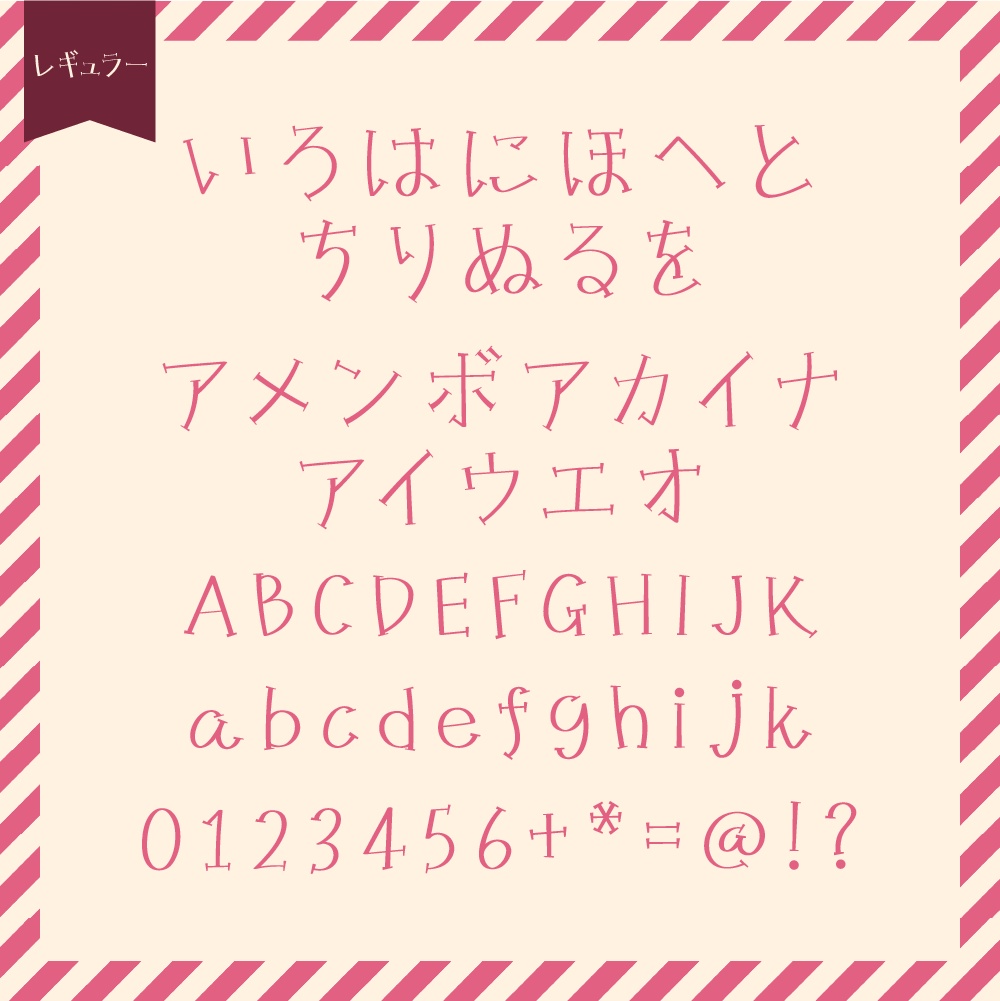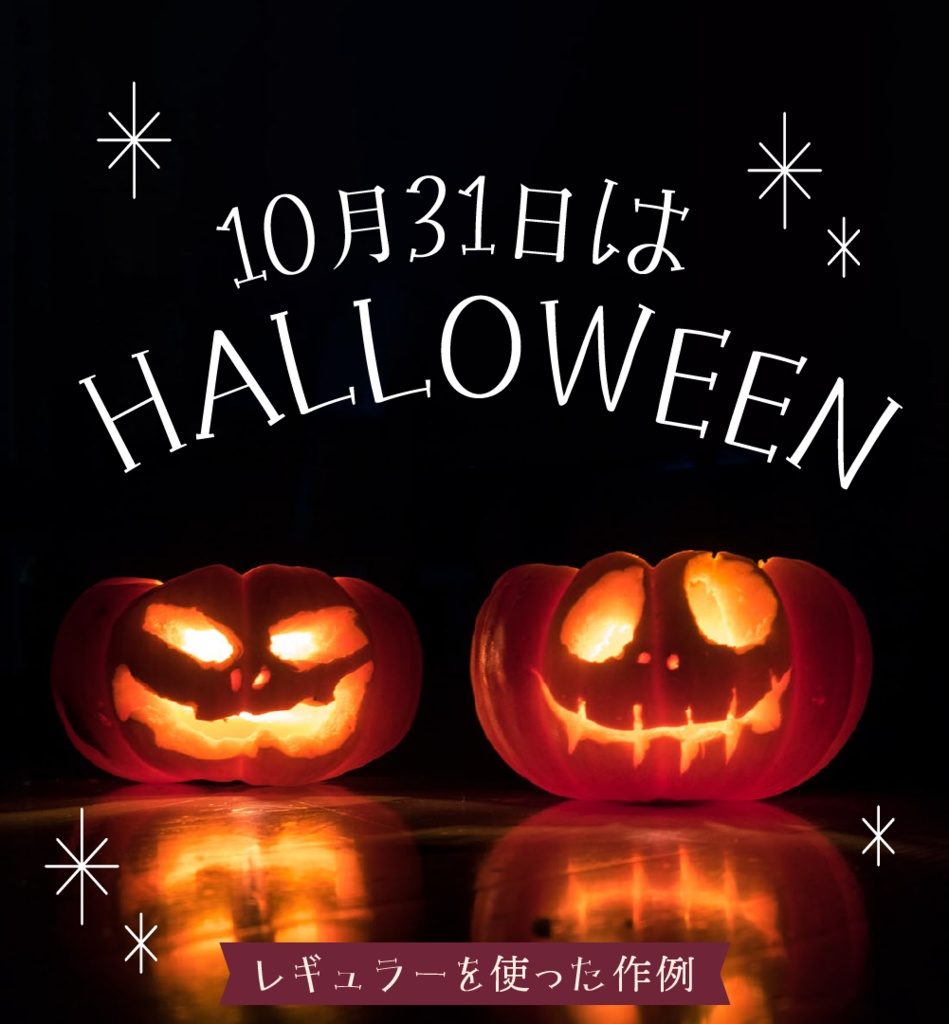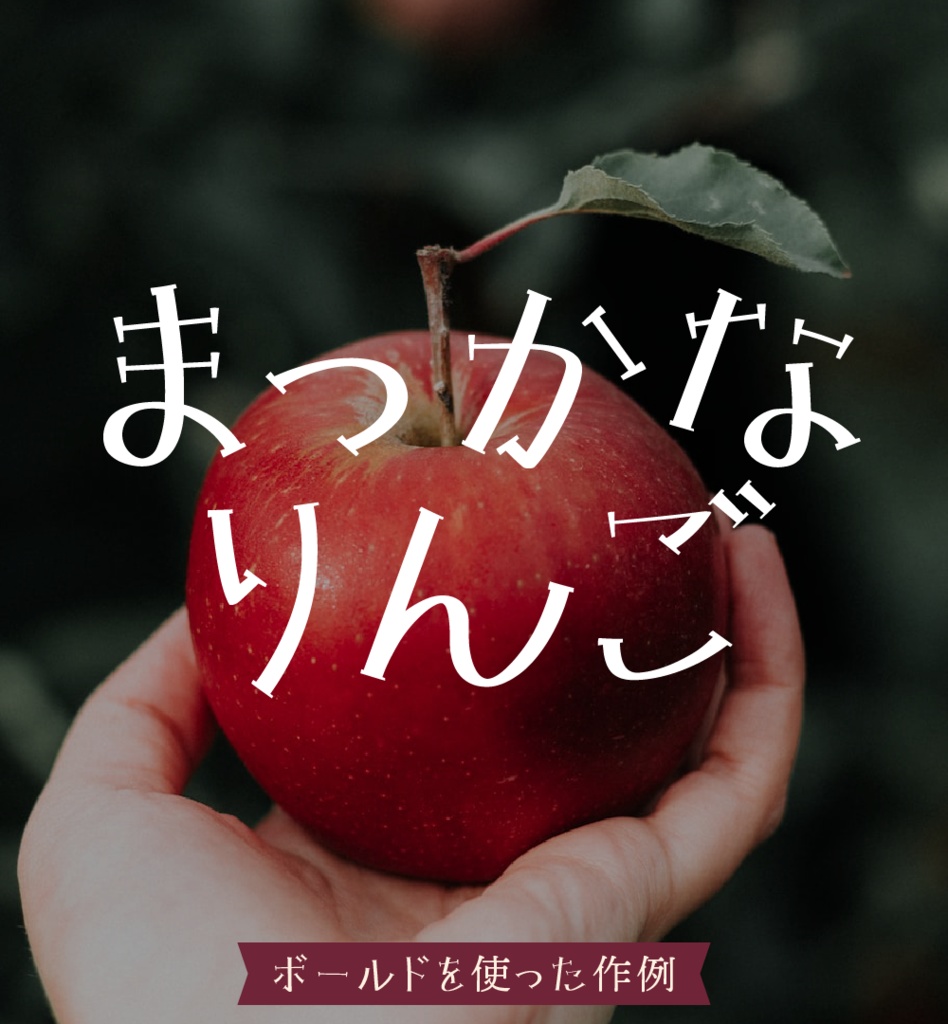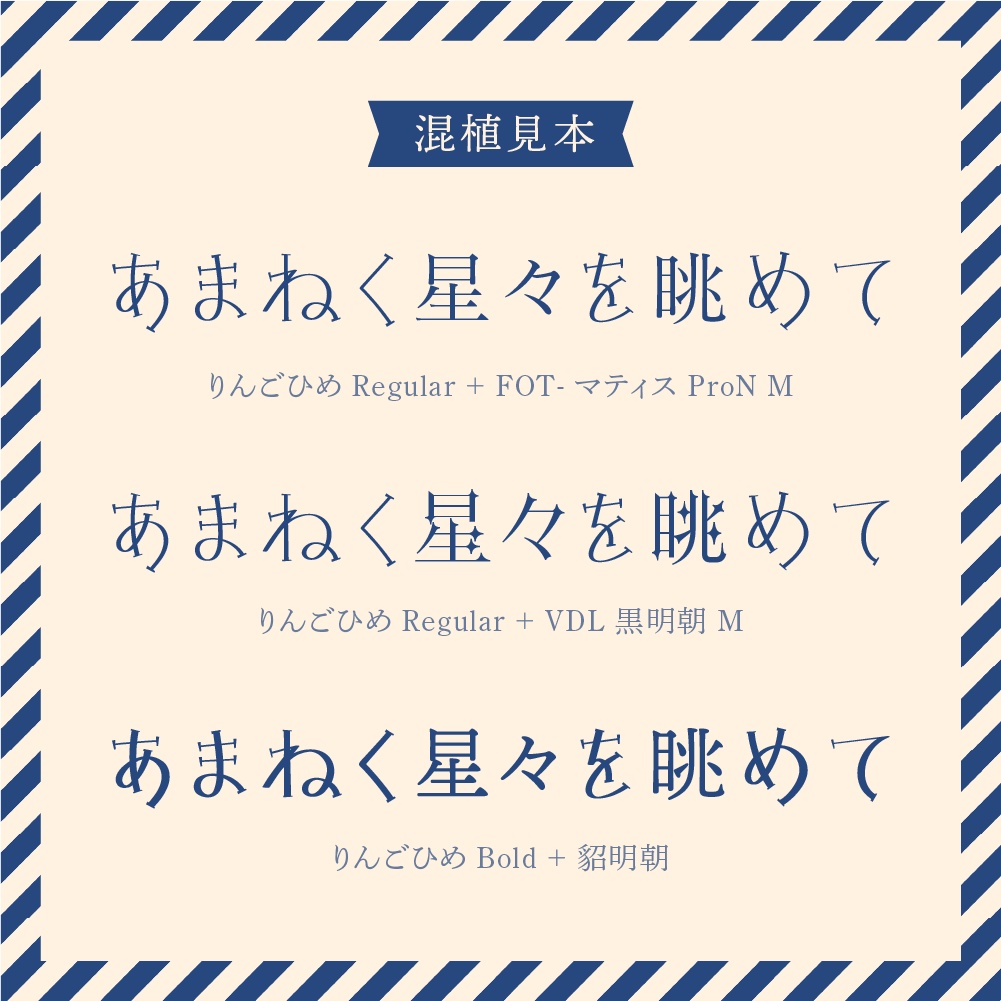
レトロキュートなフォント「りんごひめ」2ウェイトセット
かな・カナ・アルファベット・数字が使えるフォント「りんごひめ」です。
どんなフォント?
手描き文字をベースに、昭和の少女向け雑誌のロゴのようなイメージで作った日本語OpenTypeフォントです(漢字なし) ベタ打ちするだけでもなんでも可愛くなるフォントを目指しました。 2ウェイト(レギュラー・ボールド)入っており、ひらがな、カタカナ、アルファベット、数字、一部の記号が収録されています。 また商用フリーとなっております。
他フォントの漢字との組み合わせ
「りんごひめ」には漢字は収録されておりません。 混植見本ではAdobe fontsの日本語フォントと組み合わせてみました。 細めの明朝と相性が良いです。